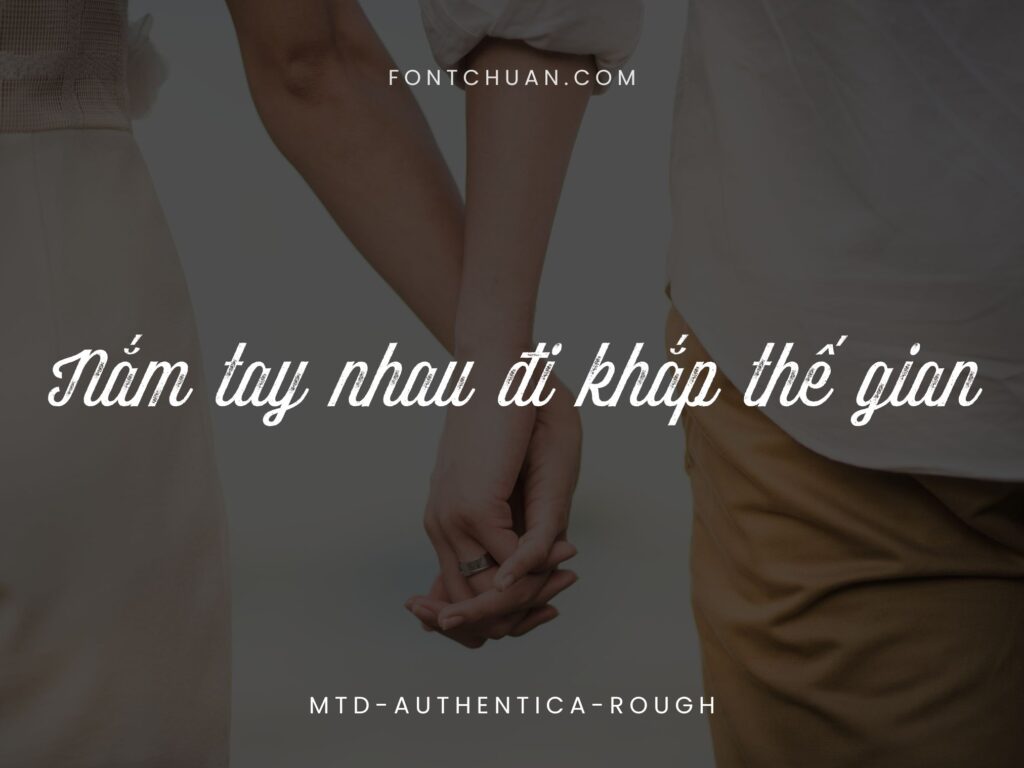
Font MTD Authentica Rough Việt Hóa
Authentica là một font chữ hiện đại được thiết kế bởi Abdillah, ra mắt vào khoảng tháng 3 năm 2022. Font này mang phong cách calligraphy đơn giản và tinh tế, phù hợp cho nhiều mục đích thiết kế khác nhau. Để hỗ trợ cộng đồng thiết kế Việt Nam, Mộc Hạ đã Việt hóa font Authentica, giúp font này tương thích hoàn toàn với tiếng Việt và hơn 200 ngôn ngữ khác. Font Authentica Việt hóa được sưu tầm và chia sẻ bởi các thành viên của Font Chuẩn, nhằm đáp ứng nhu cầu đa dạng của người dùng và ứng dụng thực tế trong các dự án thiết kế.
Về đặc điểm thiết kế, Authentica sở hữu các đường nét mềm mại, uyển chuyển với cấu trúc chữ mượt mà và độ tương phản nhẹ. Font này bao gồm các ligatures tinh tế, tạo sự liên kết hài hòa giữa các ký tự, mang lại cảm giác tự nhiên và thân thiện. Authentica đặc biệt phù hợp cho các thiết kế thiệp mời, logo, tiêu đề, và các dự án nghệ thuật chữ. Ngoài ra, font này cũng thích hợp cho các ngành nghề như quảng cáo, thiết kế thiệp cưới, và ẩm thực, nơi cần sự sáng tạo và phong cách độc đáo.